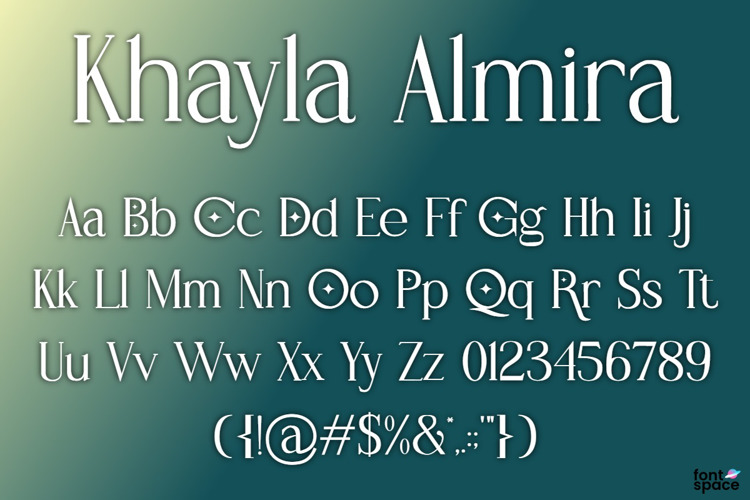
Khayla Almira Font
Khayla Almira adalah font penanda menetes yang sempurna untuk digunakan dalam poster, pajangan, proyek branding, logo, papan nama, poster, undangan, dan lainnya. Ini adalah font penanda bertekstur indah yang memberikan goresan bertekstur alami.